Con este curso de Domestika aprenderás a crear diseños de tipografías a partir de cuadrículas y dales vida con técnicas de animación procedural y aleatoria.
¿Te gustaría aprender a transmitir conceptos complejos de una manera visualmente atractiva y comprensible? En este curso online, el diseñador interdisciplinar y artista digital Martin Naumann te mostrará cómo crear diseños tipográficos basados en cuadrículas y cómo animarlos empleando métodos procedurales y aleatorios.
Sus piezas se caracterizan por poseer colores vivos y una estética futurista, y a lo largo de su carrera ha colaborado en proyectos galardonados para clientes como Die Zeit o la marca de chocolate Laroché, así como para los sellos discográficos Universal Music y Anjunabeats. Únete a él en este emocionante viaje, déjate seducir por el azar y crea impresionantes animaciones gráficas.
Al principio del curso conocerás al diseñador interdisciplinar y artista digital Martin Naumann. Tras hablarte de su trayectoria profesional, compartirá contigo sus principales fuentes de inspiración.
En la segunda unidad, Martin te explicará los conceptos básicos y la terminología de los campos del diseño tipográfico y el arte generativo. Después, te familiarizarás con la teoría del color y crearás un mood board con referencias para el diseño de tu tipografía. Tras ello, elegirás una palabra o letra como motivo de base para tu pieza.
A continuación, tu profesor te enseñará cómo diseñar y exportar los vectores de tus letras en Adobe Illustrator, para luego poder trasladarlos a After Effects. En este último software, verás algunos efectos de distorsión y degradados procedurales y cómo aplicarlos a tu proyecto.
Llegado este punto, Martin te mostrará cómo generar y animar texturas de colores aleatorios para aportar a tus letras una estética vibrante. Para acabar este apartado, te indicará cómo exportar las animaciones individuales en formato de video o en una serie de imágenes generativas y juntarlas en un único diseño.
Por último, conocerás algunos plug-ins para After Effects y el programa Filter Forge, que puedes usar para realizar proyectos similares.
A partir de una palabra o letra como motivo central, crearás diseños de tipografías abstractos y elaborarás un porfolio de efectos que podrás utilizar en módulos.
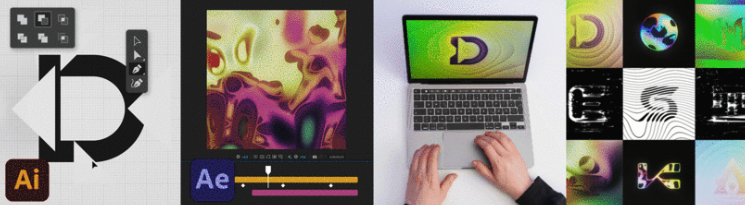
A cualquier persona interesada en el diseño experimental de tipografías, la animación o el arte abstracto digital y que desee acercarse a estas disciplinas.